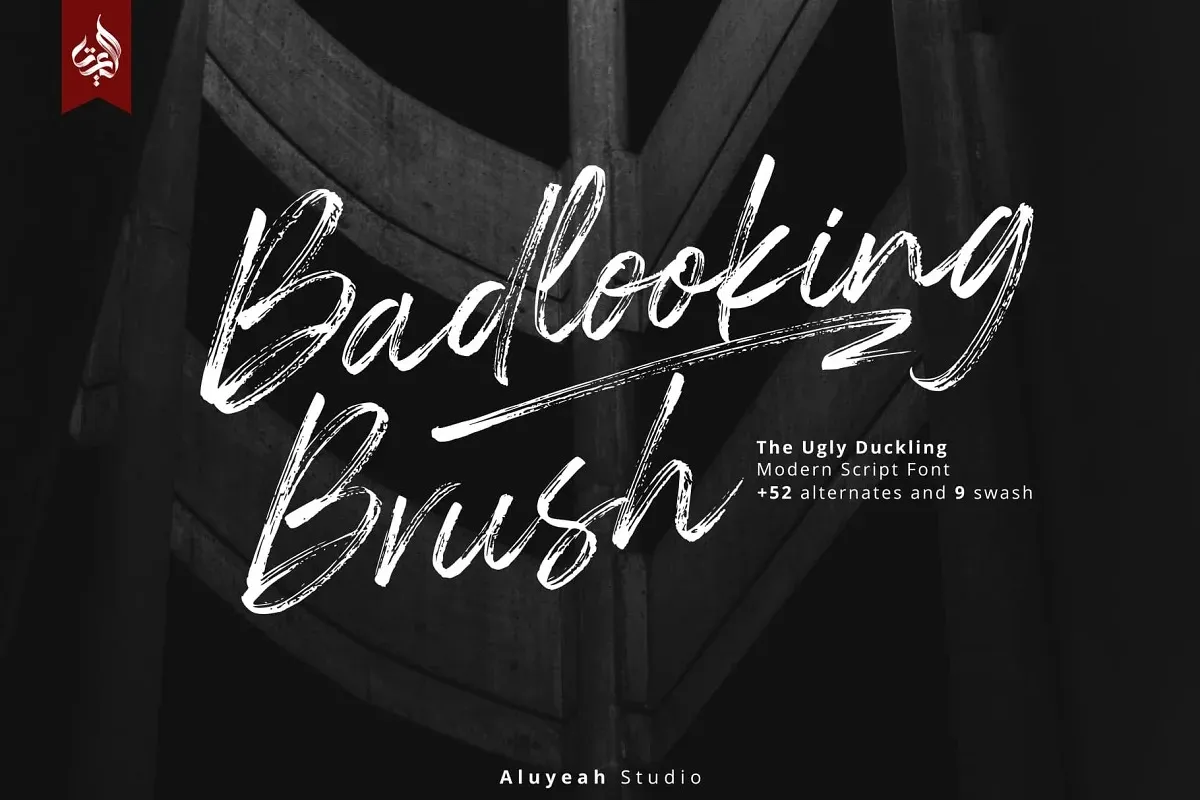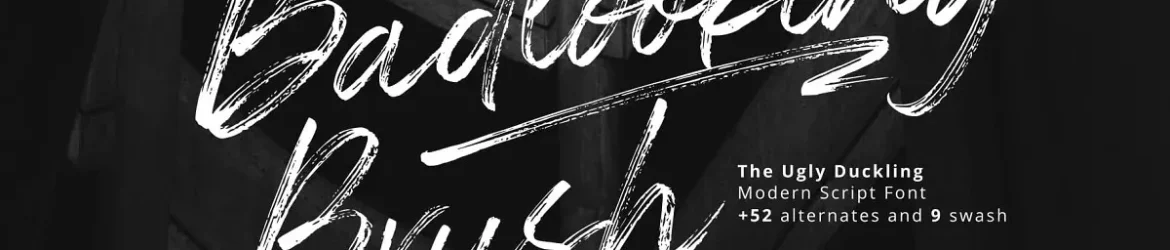
Badlooking Brush Font – Download Grátis
A fonte ‘Badlooking Brush Font’ é uma criação única do Aluyeah Studio, apresentando belos caracteres cuidadosamente projetados à mão. Esta fonte foi criada com um pincel e água-base de alta qualidade, proporcionando um estilo elegante que certamente fará seu design se destacar. Inclui 52 alternativas de texto, junto com 9 belas traçadas e alternativas super fáceis de usar. Seja você designer de aplicativos móveis ou criador de sites, ‘Badlooking Brush Font’ é uma fonte versátil que garantirá um toque único ao seu trabalho. Agradecemos pela escolha deste deslumbrante recurso gráfico do Aluyeah Studio para tornar sua obra ainda mais memorável.